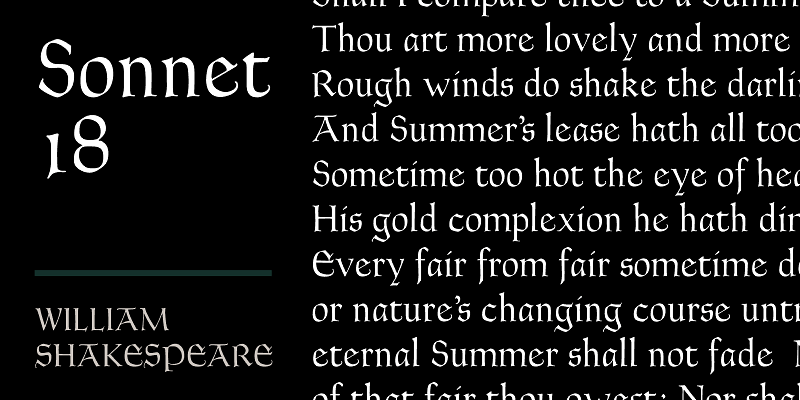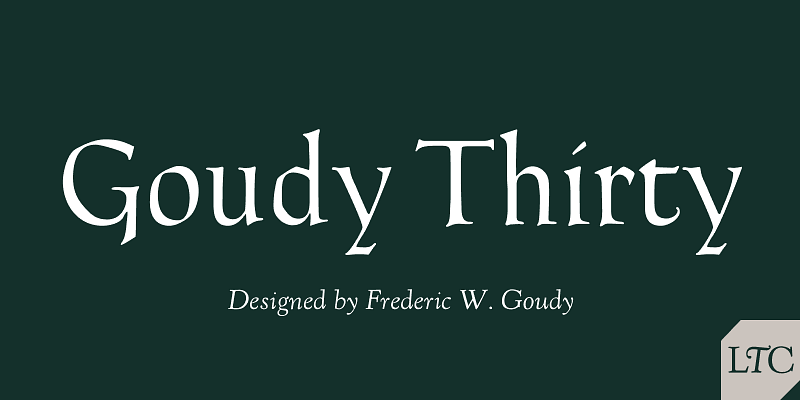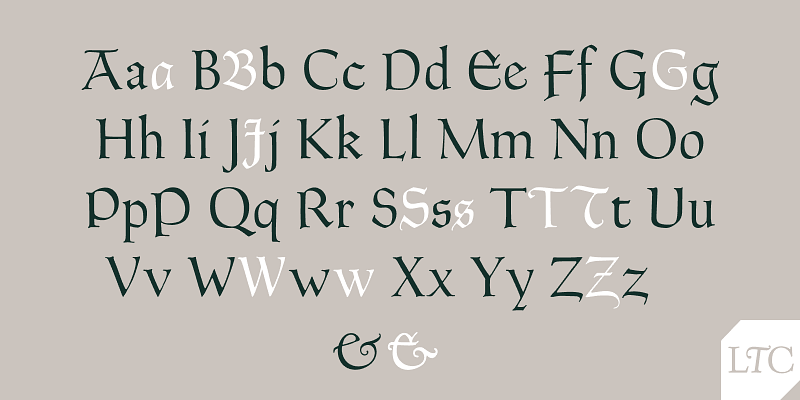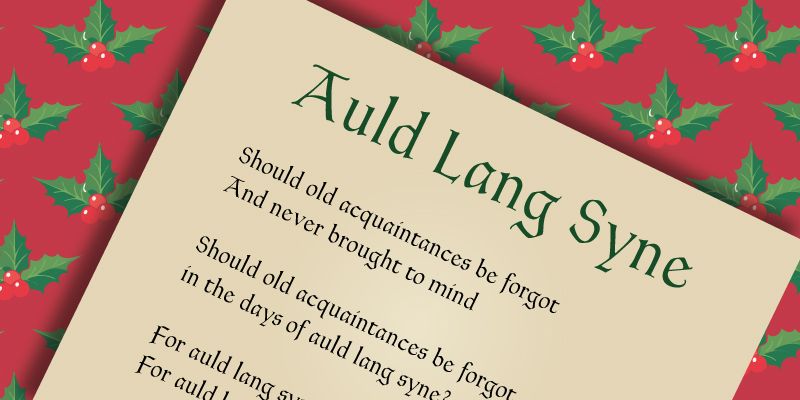
Die Antiqua-Schrift LTC Goudy Thirty weist, ähnlich wie andere Goudy-Schriften, charakteristische, leicht gotisch angehauchte Details auf. Der amerikanische Schriftdesigner und Typograf Frederic W. Goudy (1865–1947) entwickelte sein Design ursprünglich als Schrift für eine private Druckerei, die eine Hochschule im Westen der USA ausstatten wollte. Das Projekt wurde jedoch nie abgeschlossen. Die Lanston Monotype Company schlug Goudy vor, die Schrift nach seinem Tod unter dem Namen „Goudy Thirty“ zu veröffentlichen. Die Zahl „Thirty“ bezieht sich auf den aus dem Journalismus stammenden Begriff „-30-“, der das Ende einer Meldung oder Geschichte kennzeichnet. Goudy Thirty wurde 1942 entworfen. Goudy starb 1947 und Lanston Monotype brachte die Schrift 1953 auf den Markt.
Die Wurzeln von Lanston Type Co. (LTC) gehen auf die Lanston Monotype Company von 1887 zurück, die von Tolbert Lanston, dem Erfinder der Monotype-Gießmaschine, gegründet wurde. Nach der Trennung von seinem englischen Pendant hatte LTC Probleme und wurde mehrmals verkauft, an American Type Founders, Hartzel Machine Works, Mackenzie & Harris und Gerald Giampa. Im Jahr 2004 übernahm P22 Type Foundry die Firma und beherbergt heute klassische Designs von Frederic W. Goudy und Sol Hess sowie die neueren zeitgenössischen Meister Giampa, Jim Rimmer und Dave Farey.